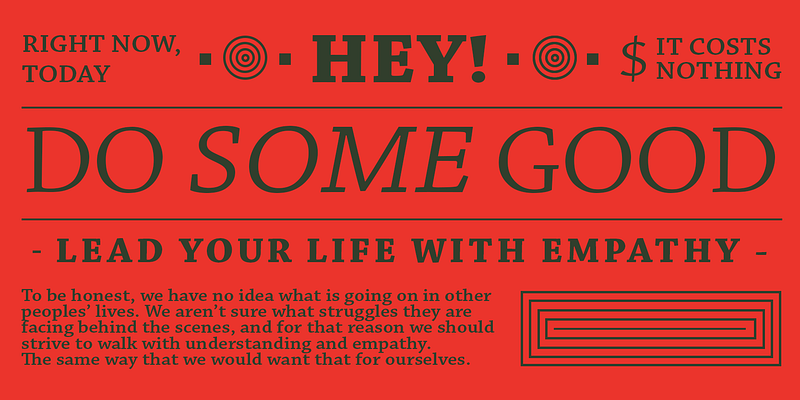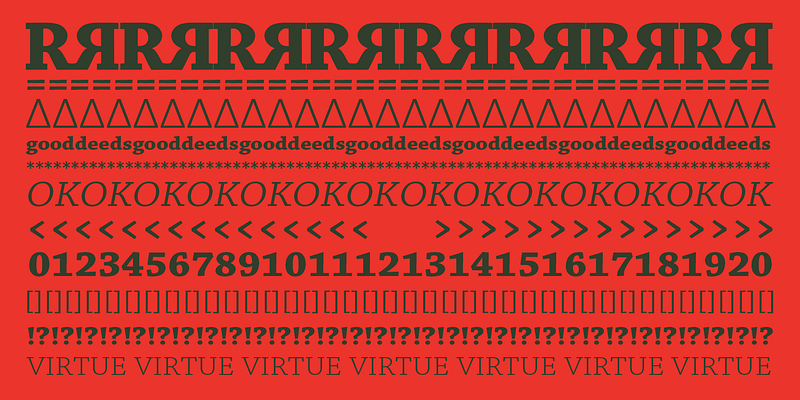
Creada por la diseñadora tipográfica de Adobe Carol Twombly, Chaparral combina la legibilidad de los diseños de slab-serif popularizados en el siglo XIX con la gracia de la letra de libro romana del siglo XVI. El resultado es un diseño versátil e híbrido de slab-serif, una adición única a la familia de tipos de letra de Adobe Originals. A diferencia de los diseños Slab Serif “geométricos“, Chaparral tiene unas proporciones de letra variables que le dan un aspecto accesible y agradable en todos los grosores, desde los ligeros hasta los más gruesos. Y como se trata de un tipo de letra múltiple con un eje óptico (que oscila entre 7 y 72 puntos), Chaparral es clara y legible en configuraciones de texto más pequeñas, a la vez que sigue siendo sutil y viva en tamaños de pantalla. Al igual que los arbustos resistentes a la sequía que florecen en la árida cordillera costera cercana al hogar de Twombly en California, el diseño altamente funcional de Chaparral es sorprendentemente bello, la elección perfecta para la correspondencia, así como para el diseño de libros, carteles y boletines.